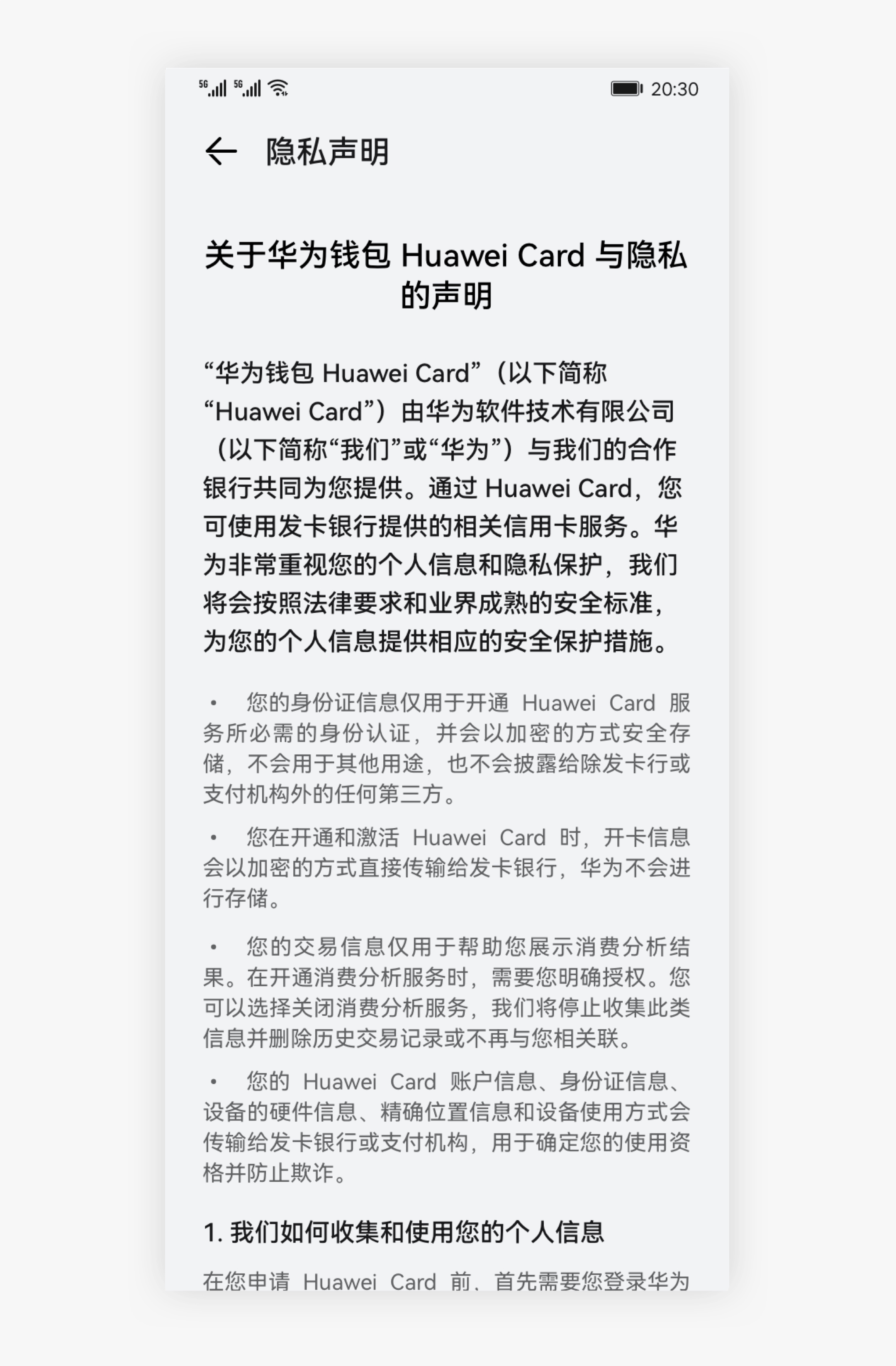
关于 HarmonyOS Sans
华为鸿蒙字体 (HarmonyOS Sans) 是华为和汉仪字库合作定制,专门为鸿蒙操作系统设计打造,设计上聚焦于功能性、普适性,字形和之前介绍过的谷歌思源黑体、阿里巴巴普惠体以及 OPPO 手机公司的 OPPO SANS 等免费商用字体有点类似,是一款适合阅读的多字重中性字体。
HarmonyOS 字体特性
5种字重粗细调节。HarmonyOS Sans 支持可变特性,让用户选择他们喜欢的字体粗细来进行文本的显示。
支持等宽与变宽两种样式。变宽数字在阅读文本段落中能让阅读体验更加连贯。而等宽数字在强调数值以及数据需要经常变化的表格、时钟数字的 UI 界面使用时,效果会更好。
支持多国语言。HarmonyOS Sans 支持简体中文、繁体中文、拉丁、西里尔、希腊、阿拉伯等5大书写系统,105种语言全球化覆盖。
支持更多字重能力
HarmonyOS Sans增加了Thin、Light、Bold、Black的字重能力,开发者可以选择需要的字重来构建界面的信息层级。
等宽与变宽数字字体
HarmonyOS Sans支持变宽和等宽两种样式。文本混排中使用系统默认的变宽数字,在阅读文本段落中能让阅读体验更加连贯。而等宽时钟数字在需要强调数值以及数据需要经常变化的表格和时钟数字的场景中使用时,可以保持数字字宽的对齐,同时更具图形化的呈现可以在界面中脱颖而出。
支持时钟字体特性
HarmonyOS Sans支持时钟字体特性,冒号格式会根据时间格式自动调整位置。
通用性极佳,中英文混排效果优秀。鸿蒙系统是一款面向全场景的分布式操作系统,无论在手持设备、电视大屏幕还是手表的小屏上, HarmonyOS Sans 鸿蒙字体都具备极强的通用性和协调性。无论是粗体还是细体均需拥有出色的一致性。
字体排版
多设备字号层级
选择合适的字号有助于定义内容的信息层级,以及达到内容的可读性。通过研究全场景设备的显示环境、用户使用时环境的差异,我们为不同设备形态定义了一套构建信息层级的字号系统。
文本对齐规则
不同的文本对齐方式可以引导用户的视觉流向。在段落文本中文本超长换行默认使用左对齐的方式,因为人的浏览视线都是从左往右移,因此大段需要阅读的文案,采用左对齐的方式排版有利于用户快速定位,保证良好的阅读体验。相对于更常见的左对齐,居中对齐可以更容易获得用户的注意力,因此在标题上、空页面的描述文本以及在插画的引导页上使用居中对齐可以更有效地抓住用户眼球。
居中对齐可以更容易获得用户的注意力 左对齐的方式排版有利于用户快速定位